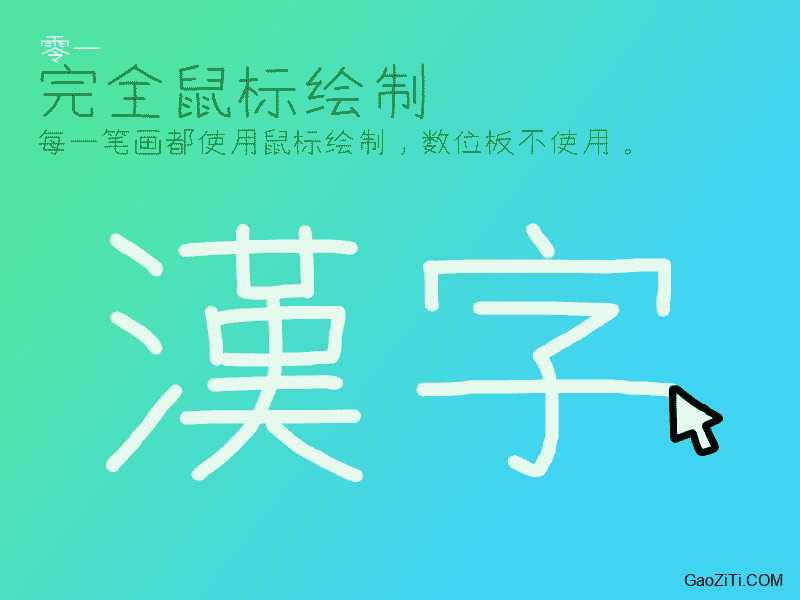
快去写作业CJK
完全用鼠标构建字形的“仿”手写体
字体介绍
快去写作业CJK(CEF Fonts CJK)是一个完全用鼠标构建字形的“仿”手写体。本字体最大的特点就是里面的绝大部分字形均由鼠标绘制。目前已对CJK统一汉字区块(20992个字)、谚文音节(全部11172个)提供主要支持, 可以为简繁中文、日语、韩语、英语、希腊语、俄语、泰语(仅字符)等部分语言提供基本显示。